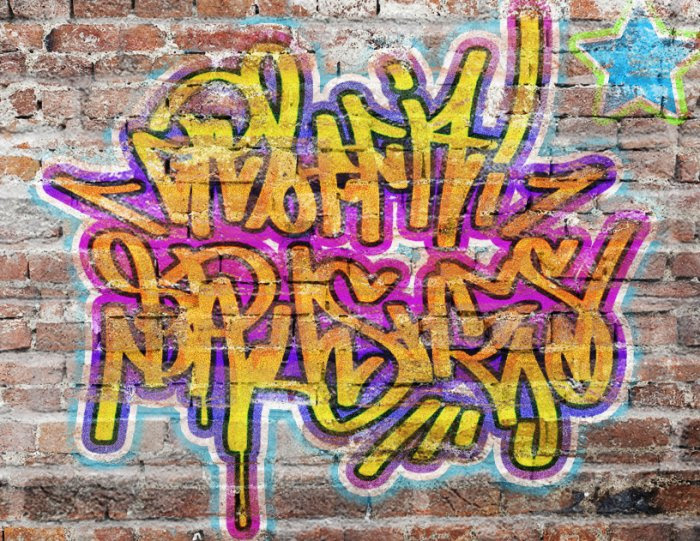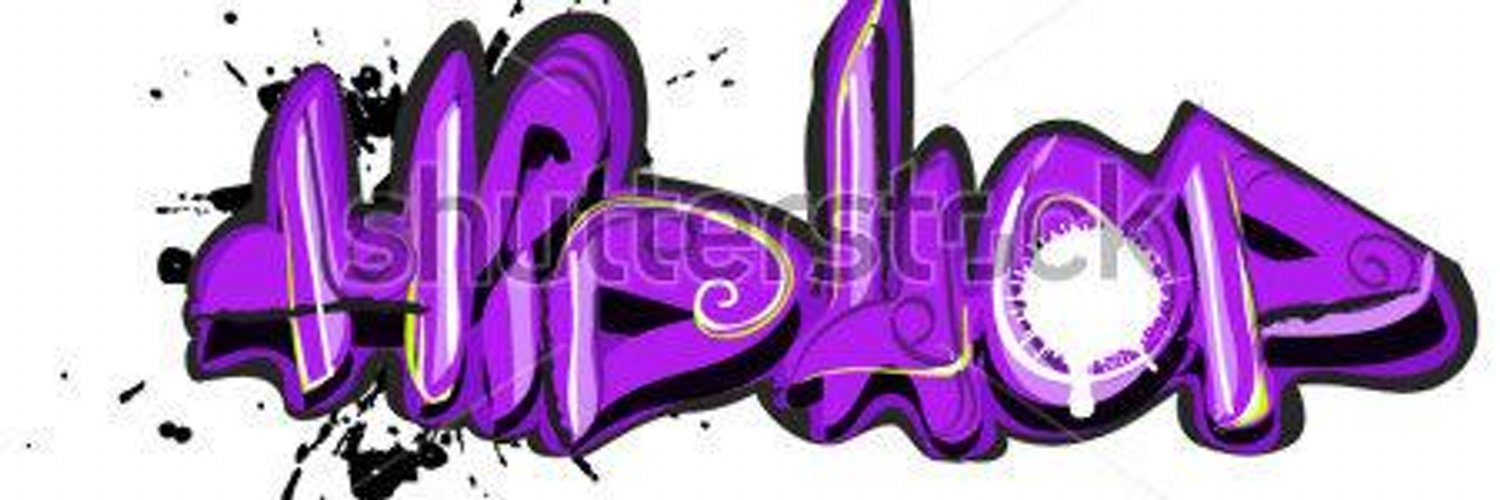
PhotoshopSunduchok — Текст в стиле «Граффити»
Сегодня мы будем создавать текст в стиле «Граффити» на стене.
Для того, чтобы написать текст на стене при помощи краски, нам не понадобится тратиться на краску и искать под покровом ночи свободную стену для разрисовки.
Все, что нам нужно – это программа фотошоп, немного свободного времени и желание сотворить что-то интересненькое!
В данном уроке мы будем пользоваться неразрушающими методами обработки, которые позволят в любой момент регулировать настройки.
Сначала мы откроем фотографию со стеной из папки с исходниками и при помощи корректирующих слоев Черно-белое и Уровни обесцветим стену – на темном фоне эффект будет лучше смотреться.
Затем мы установим шрифт из папки с исходниками, при помощи инструмента Текст напишем текст и применим к текстовому слою стили слоя, чтобы придать тексту эффект разбрызганной краски.
В завершение мы создадим дубликат текстового слоя, изменим в нем текст и поменяем оттенки текста на обеих слоя с текстом.
Открываем в фотошоп (Ctrl+O) изображение с текстурой стены из папки с исходниками.
Добавляем корректирующий слой Черно-белое.
Настройки в окне корректирующего слоя не меняем, оставляем те, что установлены по умолчанию.
Добавляем корректирующий слой Уровни и вводим настройки, как на рисунке ниже.
Активируем инструмент Текст и пишем слово «Photo».
В верхней панели настроек инструмента Текст выбираем шрифт, что установили в предыдущем шаге, увеличиваем размер текста, меняем цвет текста на белый (# ffffff) и вводим настройки, как на рисунке ниже.
При помощи инструмента Перемещение располагаем текст, как на рисунке ниже.
В уроке текст в стиле «Граффити«, вызываем Свободное трансформирование (Ctrl+T) и, зажав клавишу Shift (для сохранения пропорций) и Alt (чтобы трансформирование происходило из центра), тянем за уголки рамки, чтобы увеличить текст.
Располагаем текст на холсте, как на рисунке ниже.
В панели слоев понижаем заливку текстового слоя.
После этого слой с текстом станет невидимым.
В панели слоев дважды кликаем по текстовому слою, чтобы открыть стили слоя.
Во вкладке Тень меняем оттенок тени на белый (# ffffff).
Кликаем по треугольнику и строки выбора контуров и из выпадающего списка выбираем контур, как на рисунке ниже.
Полные настройки для вкладки Тень на втором скриншоте.
Результат после применения стилей слоя.
В реальности краска на стену ложится неравномерно.
Чтобы создать эффект неравномерности текста на кирпичах, снова заходим в стили слоя на текстовом слое (двойной щелчок по слою в панели слоев).
Во вкладке Параметры наложения тянем левый ползунок на нижнем градиенте вправо и следим, как будет меняться текст.
Когда результат устраивает, зажимаем клавишу Alt и «разделяем» ползунок.
Тянем раздвоенную правую часть ползунка вправо, чтобы создать плавный переход на текстовом слое.
Результат после применения стилей слоя.
В панели слоев создаем дубликат текстового слоя (Ctrl+J).
Дважды кликаем по иконке копии текстового слоя в панели слоев, чтобы редактировать текст.
Меняем текст на «shop» и при помощи инструмента Перемещение располагаем текст в нижней части холста.
При помощи инструмента Перемещение подкорректируем расположение обеих слоев с текстом.
Осталось только изменить цвет текста.
Для этого дважды щелкаем по текстовому слою в панели слоев, чтобы открыть стили слоя.
Во вкладке Тень меняем оттенок для тени. Я использовала для слоя «Photo» оттенок #fbda22, а для слоя «shop» оттенок #c105c3.
Вы можете подобрать другие оттенки на свое усмотрение.
Вот что получилось у меня в результате.
Вот мы и создали эффект текст в стиле «Граффити«.
Отличного настроения и творческих успехов!
Граффити на стене — Уроки фотошоп и все о фотошоп
В этом уроке Фотошоп, мы рассмотрим способ нанесения граффити на стену.
Шаг 1. Откройте изображение в Фотошоп.
Шаг 2. Прежде всего нам нужно создать эффект нарисованной картинки. Итак, создайте дубликат слоя (Ctrl+J).
Шаг 3. Затем к дубликату слоя примените: Фильтр>Стилизация>Выделение краёв (Filter> Stylize> Find Edges). Повторите шаг3 ещё один раз.
Шаг 4. Для копии слоя измените режим наложения слоя на Перекрытие (Overlay).